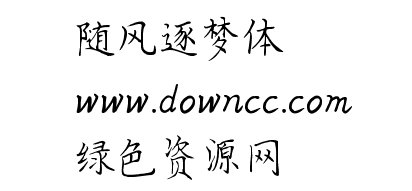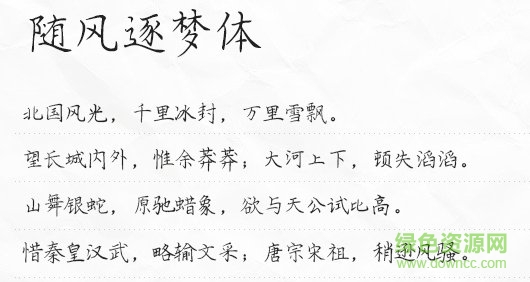
隨風(fēng)逐夢(mèng)體是一款利落爽快的硬筆手寫體,出自于思雨四庫的楷體書法字體,給人清新雅致的大方體驗(yàn),有著極佳的視覺效果,綠色資源網(wǎng)獨(dú)家推薦!
“每一次與成功的交接,必定是艱苦奮斗的汗水與不甘失敗的淚水共同鑄就的。我愿做那勇敢的逐夢(mèng)者,堅(jiān)定地追尋夢(mèng)的腳步?!薄S風(fēng)逐夢(mèng)體。
本字庫是在國(guó)家標(biāo)準(zhǔn)簡(jiǎn)體字庫GB2312所包含6763漢字的基礎(chǔ)上,又增加了近200常用字,已經(jīng)覆蓋了大陸99.75%的漢字使用頻率,足以滿足日常需求。
隨風(fēng)逐夢(mèng)字體,以楷書字體為模板創(chuàng)作而成,字庫完整,滿足日常中文簡(jiǎn)體的輸入,造型得體穩(wěn)重,十分出色,可以使用在藝術(shù)設(shè)計(jì)、海報(bào)設(shè)計(jì)、平面設(shè)計(jì)等多種場(chǎng)合。